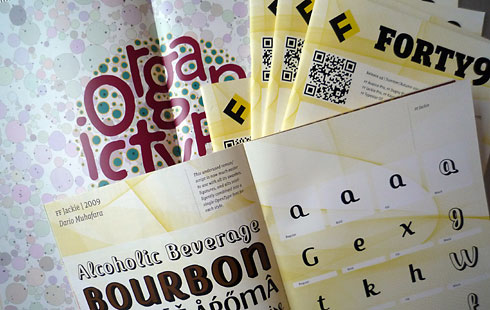
Vor 2 Monaten stellte ich hier im Fontblog unser 52seitiges digitales Schriftmustermagazin Forty9 vor (als PDF auf issu.com). Es zeigt die mit dem Release 49 erschienenen neuen FontFonts, sowohl in neutraler Darstellung als auch optisch inszeniert. Für die Gestaltung verpflichteten wir Alexander Roth, dessen Qualität Erik Spiekermann später mit diesen Worten umschrieb: »Alexander macht die besten Schriftmuster, die ich kenne seit Berthold 1913. Das liegt vor allem daran, dass er die Schriften versteht, die er abbildet.«
Forty9 war der erste Versuch von FSI und FontShop Deutschland, Abschied vom gedruckten Schriftmuster zu nehmen. Heute können wir sagen: Der Versuch ist gescheitert. »Und das ist auch gut so … « denn der Name Berthold verpflichtet schließlich. Schon der erste Kommentar zum damaligen Beitrag, abgegeben vom langjährigen Fontblog-Leser microboy, belehrte uns eines Besseren: »Gibt es die Schriftmuster auch in gedruckter Form?«. Und Lena Weissweiler fügte wenig später an: »Ganz wunderbare Arbeit. Auch ich bin dafür, sie in gedruckter Form anzubieten.«. Also, haben wir es wieder getan. Wir ließen drucken, zwischen den Jahren.
Seit heute liegen nun 5000 gedruckte Exemplare von Forty9 bei FontShop im Lager, printed in Berlin (Druckpunkt). Das Kuriose an dieser Drucksache ist ihr Editorial, in dem das Ende der gedruckten Schriftmuster angekündigt wird. Wir haben schlicht vergessen den text zu überarbeiten oder einen neuen einzusetzen. Damit ist Forty9 gleich in doppelter Hinsicht historisch
• als »nie gedrucktes Schriftmuster«, wiederauferstanden in Papierform, mit einem Totenschein als Editorial und
• als Wiederbelebung der gedruckten Schriftprobe im Berthold-Qualität.
der grund für das scheitern von forty9 bzw. das bestehen der nachfrage nach einer gedruckten version des heftes sehe ich bei der mangelnden qualität von forty9. damit meine ich nicht die schriftmuster an sich, davon habe ich keine ahnung, sondern das heft als gesamtwerk.
wenn forty9 als »Abschied vom gedruckten Schriftmuster« geplant war, kann man doch nicht ein heft mit papierformat erstellen und eine hochauflösende pdf-datei davon im internet anbieten. ist es nicht logisch, dass sich das kaum jemand gerne ansieht? (ich auch nicht)
das sehen an bildschirmen funtkioniert anders. wenn man den fontblog, so wie er ist, ausdruckt und in einem zeitschriftenladen auslegt, möchte das ja auch keiner durchlesen. auch wenn ich nicht der meinung bin, dass der fontblog über ein beispielfhaftes weblayout verfügt.
Ich muss dir, Steffen, wiedersprechen. Nicht die Online-Version ist gescheitert, nein sie ist stattdessen ein sensationeller Erfolg. Das geht nicht nur aus den überwältigenden Statistiken hervor, sondern auch aus zahlreichen positiven Rückmeldungen. Ihr Erfolg ist vielmehr der Grund, warum FontShop das Heft [welches vom Format her sowohl passend für den Bildschirm als Doppelseite – siehe Vollbildmodus –, als auch für den Druck zu Hause gleichermaßen angelegt wurde!] nun doch hat drucken lassen, was mich als Verantwortlicher des Projekts wahnsinnig freut. Was vorerst gescheitert ist – und das dürfte für die Meisten hier nun wirklich eher eine gute als schlechte Nachricht sein – ist der Abschied vom gedruckten Schriftmuster.
Ich freue mich, dass Druck eben noch nicht tot ist und uns ein Heft gelungen ist, welches sowohl am Bildschirm, als auch auf Papier funktioniert. Deshalb sitzen wir auch gerade an der nächsten Ausgabe, die übrigens wieder hochaufgelöst sein wird, denn mit Artefakten oder Sägezähnen lässt sich auch am Bildschirm eine Schrift schlecht beurteilen. FontShop und FSI sind weiterhin bemüht, Schriftmuster zu produzieren, die die aktuell sinnvollsten Möglichkeiten der Technik im Sinne aller Beteiligten nutzt. Solange Gedrucktes in diese Kategorie fällt wird es wohl auch weiterhin mit schönen Buchstaben veredeltes Papier geben.
was mich freut und was mich wundert ist, dass ihr soviele alte ‘perlen’ ausgegraben habt. teilweise sind die anwendungsbeispiele echt großartig und wirklich zu den fonts passend gestaltet. was ich mir wünsche, einen kleinen tick bibliophilere gestaltung/verarbeitung (ich weiss sowas schraubt die kosten enorm in die höhe). wannkommt eigentlich mal wieder ein neues FF einzelmuster? die sind ja auch immer recht hübsch und umfangreich gestaltet.
ich finde die ff-proben auch immer wunderbar, nur hinter den sieben bergen bei den sieben zwergen in walde usa lebt und arbeit eine typoschmiede, die alleine durch ein paar kleine bilder auf ihrer webseite jedesmal wunde knie vom »anbeten« hervorruft.
hoefler & frere jones.
Fazit: Für mich kann das Heft am Monitor betrachtet nicht mithalten. Die gedruckte Version ist ein MUSS!!!
Ich bevorzuge auch klar die gedruckte Version. Sobald man mehr als einen Abschnitt lesen muss finde ich pdf zu anstrengend.